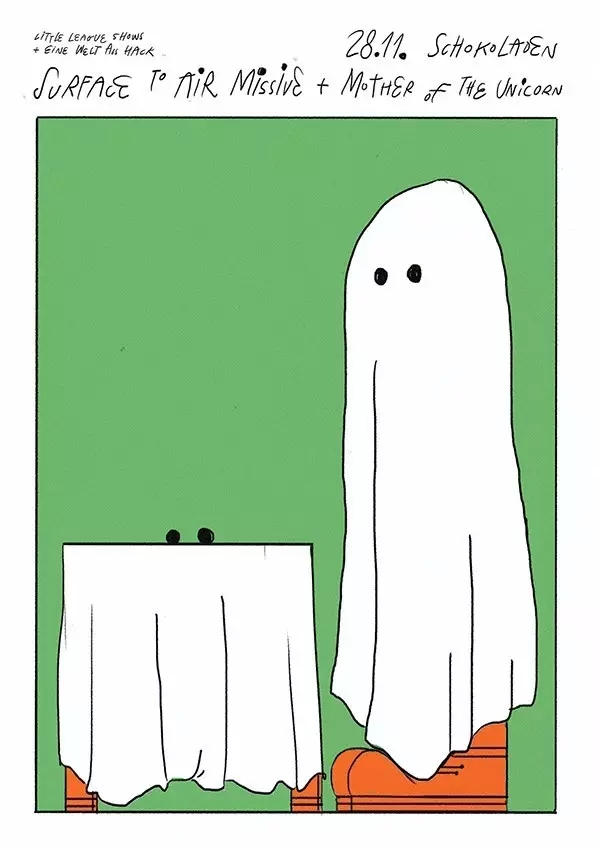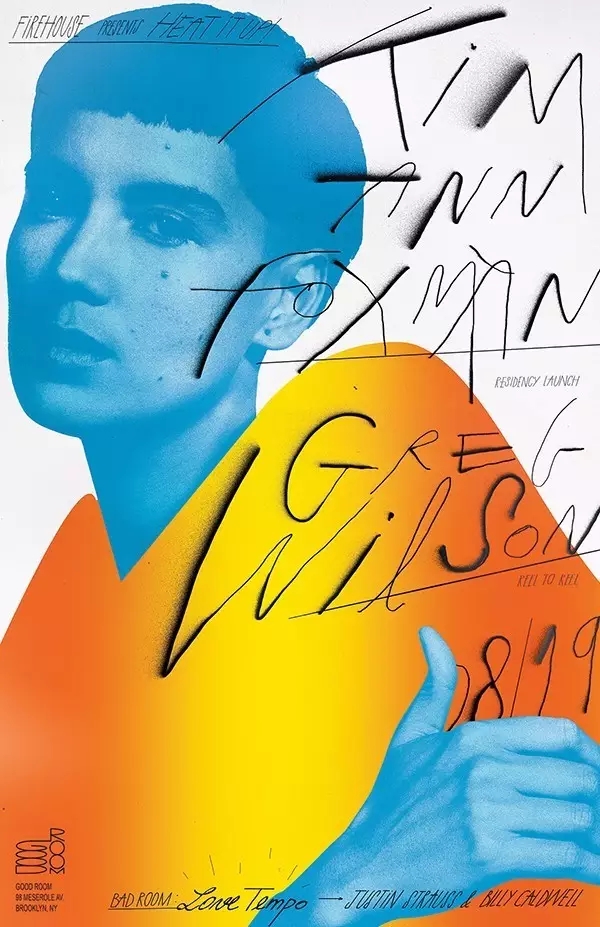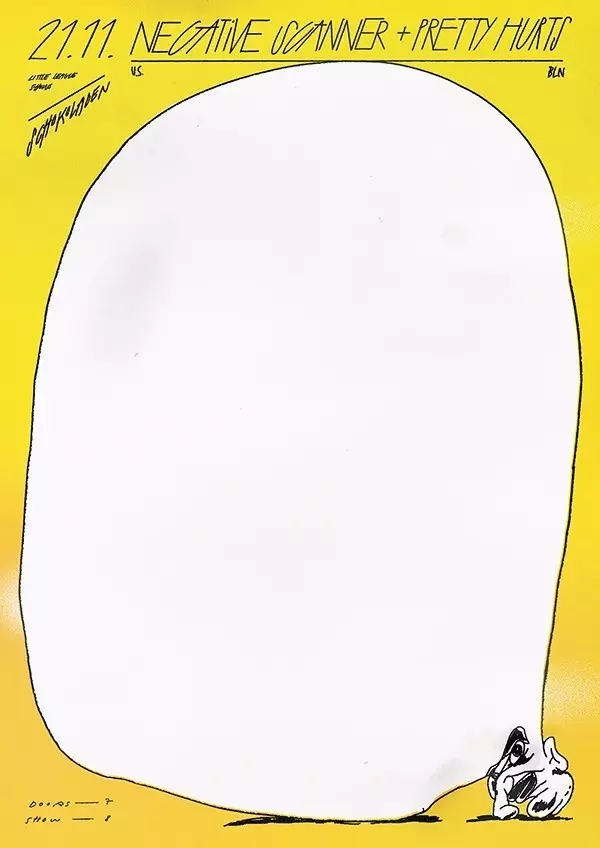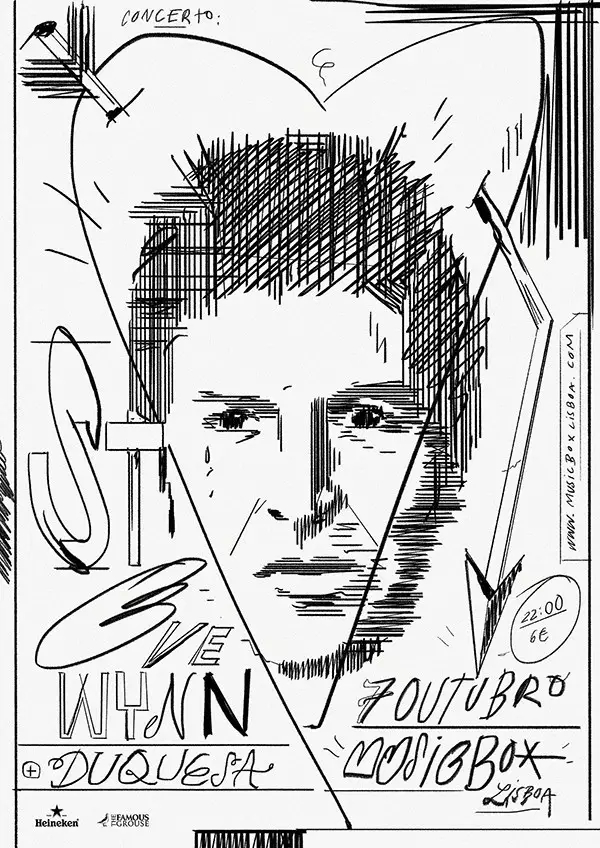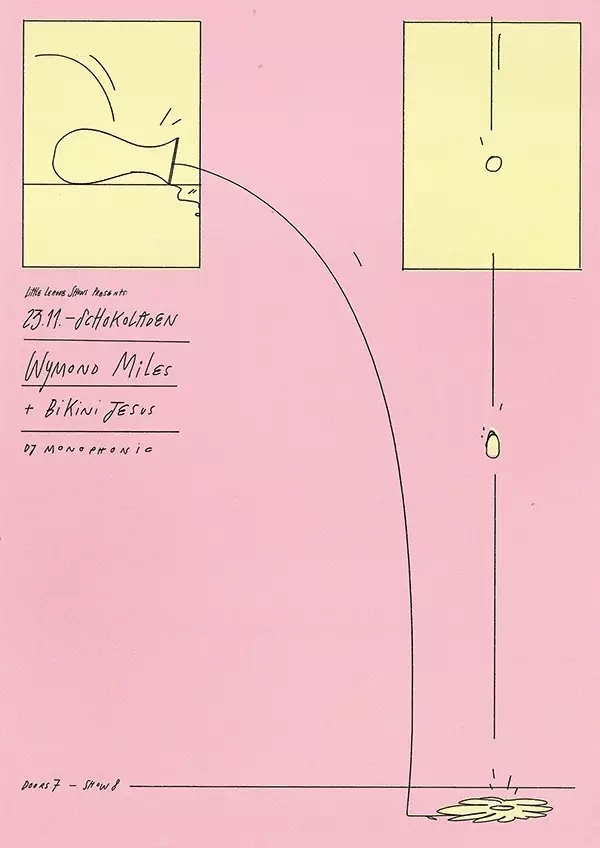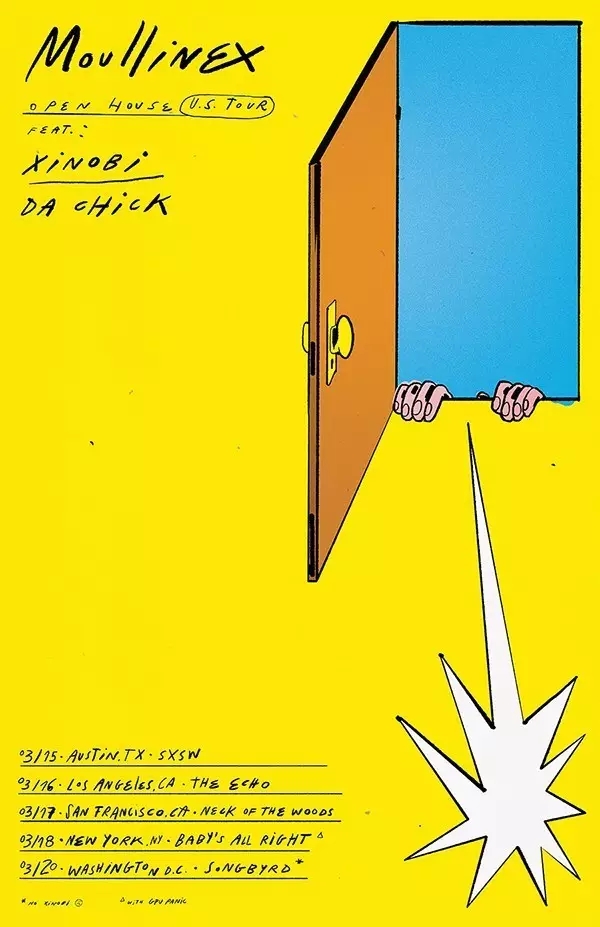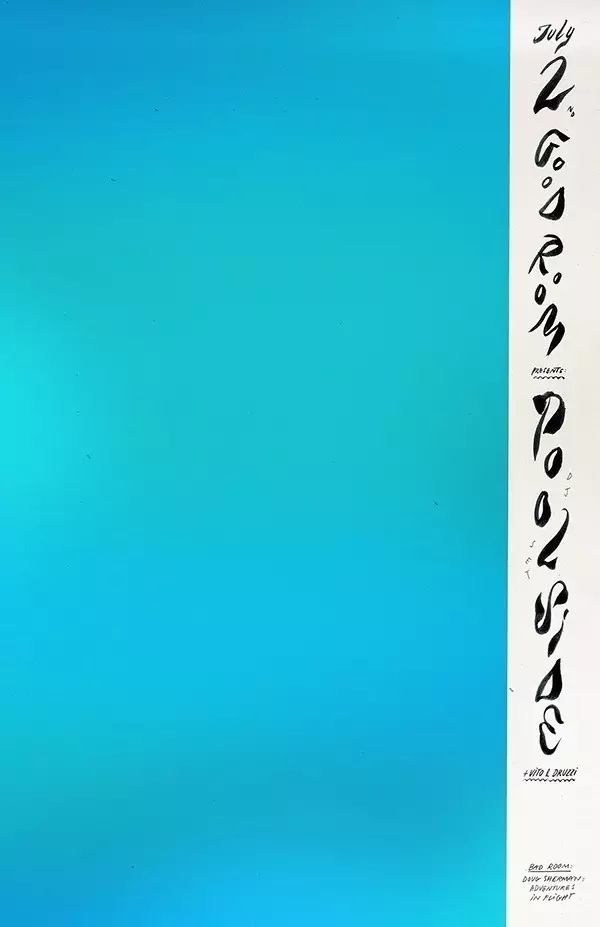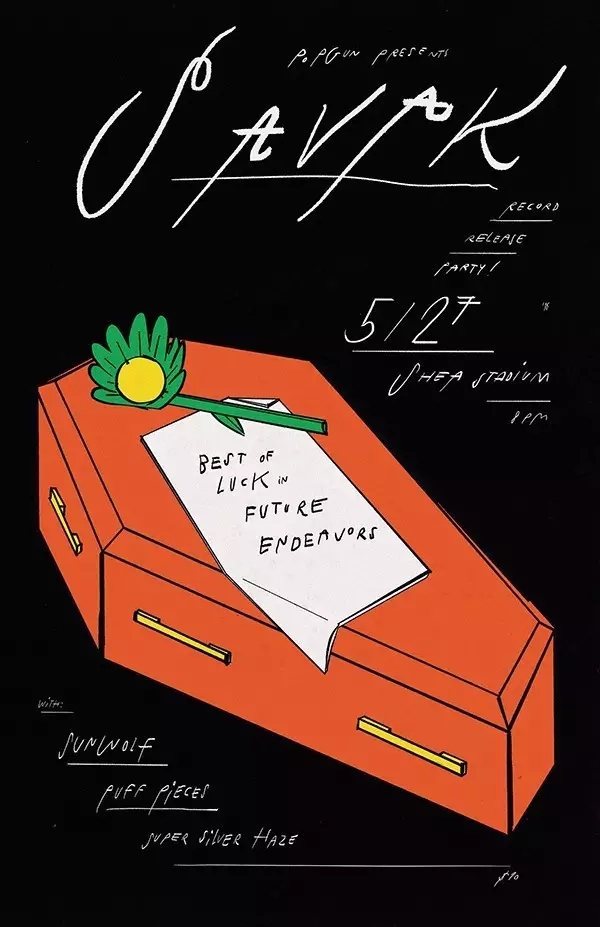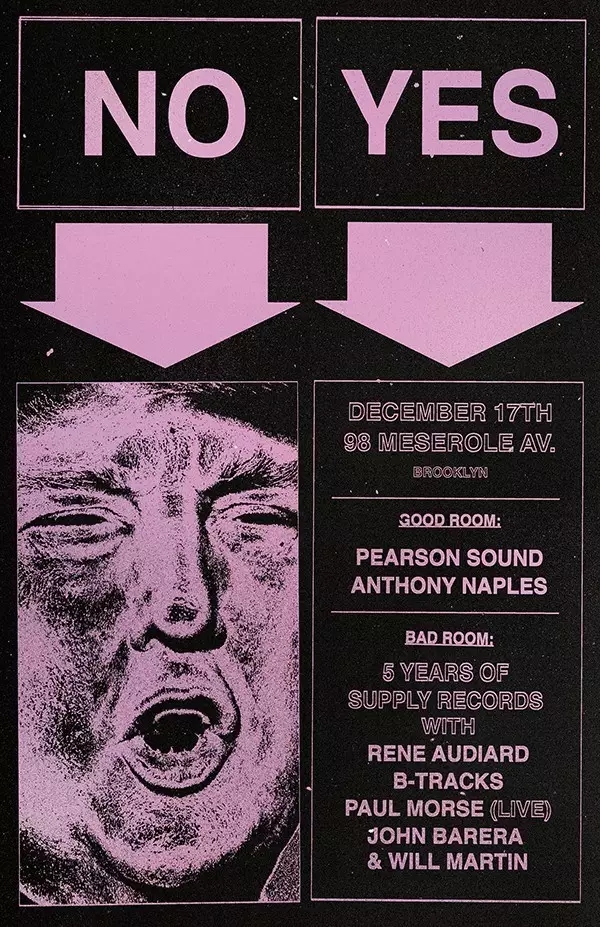
当初你想成为一名平面设计师的原因是什么?
1987年出生于 葡萄牙西部城市阿尔马达的 bráulio amado ,他是一名供职于《美国商业周刊》的平面设计师。同时,他也为许多活动和演出设计过一系列大胆精彩的海报。
在某次采访当中,designboom曾经问过他一个问题:
当初你想成为一名平面设计师的原因是什么?
braulio amado 回答说:
我绝对可以说是伴随因特网成长的一代(尽管当时的拨号速度慢如蜗牛),它也毫无疑问地成为我接触、了解和学习设计的最佳工具。我想应该是我十四岁的时候,我在雅虎地球村”(geocities)创建了自己的第一个个人主页,虽然当时只是为了好玩,可那件事却让我有了想要进一步通过软件来学习有关网页设计方面的冲动。
于是我下好了photoshop,学着怎么摆弄,然后我加入了deviantart,livejournal,做着一张张如今看上去不成体统的图,等等,等等。当时在做这些事情的时候,我的脑子里根本没有“设计”的概念,对游戏毫无兴趣的我,只是想用电脑做一些自己认为好玩的事情。而那时我的英语并不怎么样,所以大多数时候,我只能凭自己的直觉不断地进行研究和尝试,我得说那种感觉真得很棒!
几年之后,我混进了里斯本“硬核朋克”的圈子,玩音乐,排演出,给乐队画画、做海报。就是那个时候,我突然意识到我其实很想变成一个平面设计师,于是我便从此开始进行学习。在大学的最后一年,我得到了一笔奖学金,我用它完成了自己在纽约最后一个学期的学习,并因此得到了一个在pentagram实习的机会。结果他们雇佣了我并帮我办好了签证。从那时开始,我就一直呆在了美国。
几年前我离开了pentagram,目前在《美国商业周刊》杂志工作;在个人时间里,我依然为许多乐队创作和设计艺术海报。一起来看看其作品。
关于设计中的“精”与“通”,bráulio amado 是这么看的:
对某些行业来说,在某一方面有所专长的确是件好事,可我觉得在平面设计方面,对各种知识的了解和多样性可以让你的作品变得更加有趣而丰富。
多年以前,bráulio amado 一直努力想要形成一种自己在插画和字体方面的“风格”。那时bráulio amado 曾经一度认为这些都是他的优势,能够做一些让人看了一眼就能认出是出自我笔下的作品。
可最近以来,这却成了一场最令他感到头疼的噩梦。拥有自己的风格的确很不错,可有时却也会让人感到厌倦。bráulio amado 发现做一些让人看上去很容易辨别出他的风格的东西非常容易,但却失去了很多乐趣。当然,他不得不承认,有时想要摆脱这种束缚也确实很难。